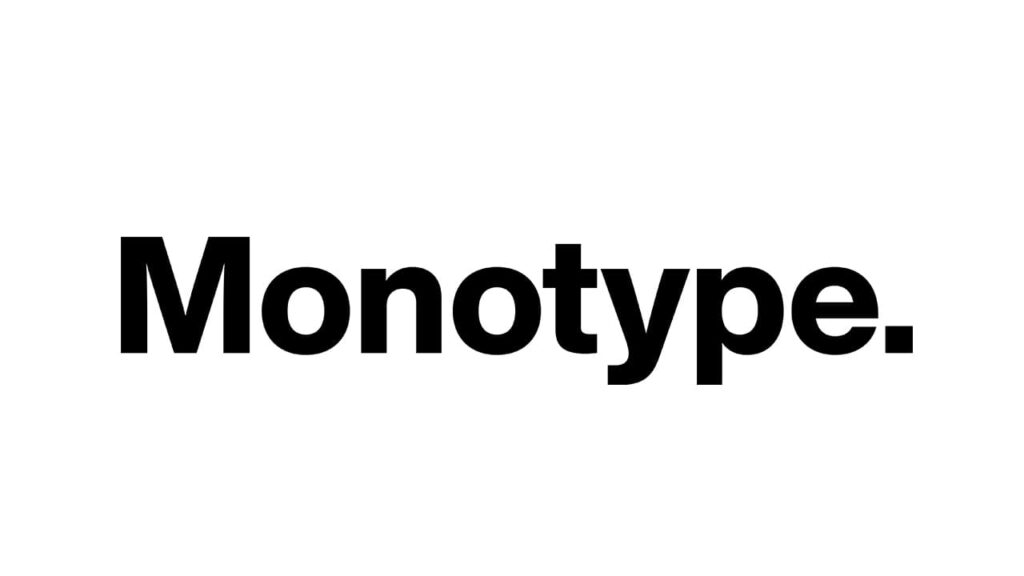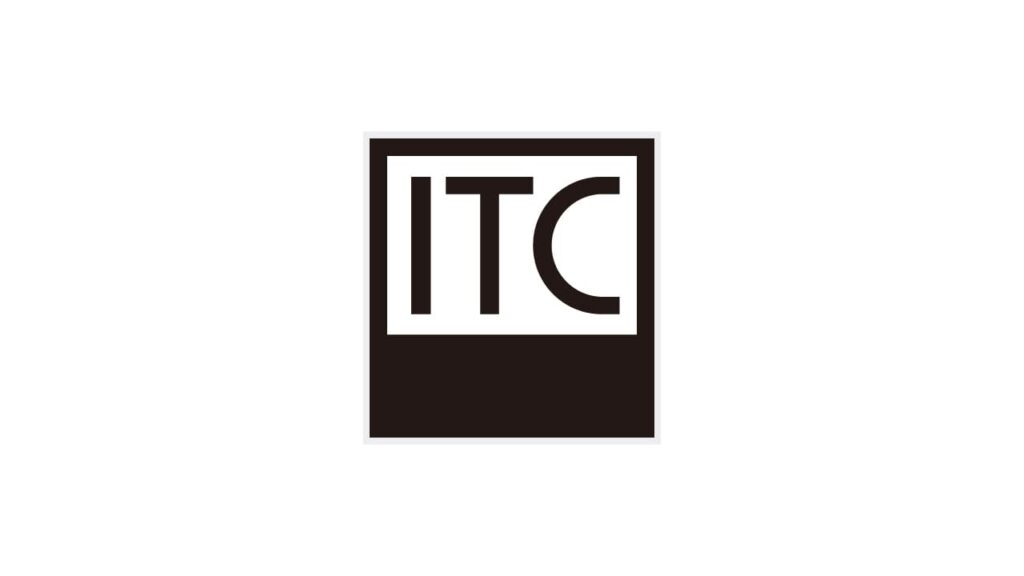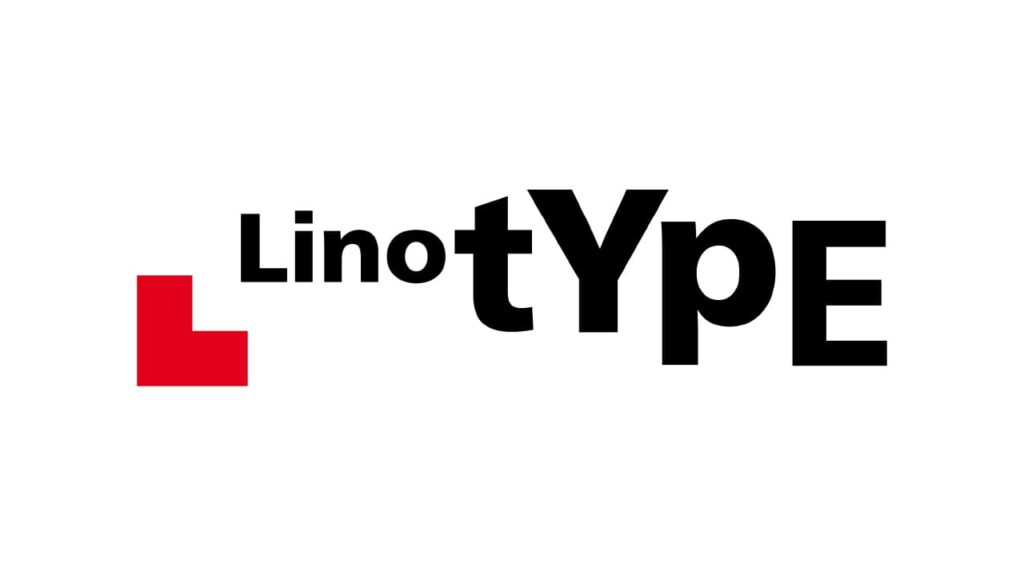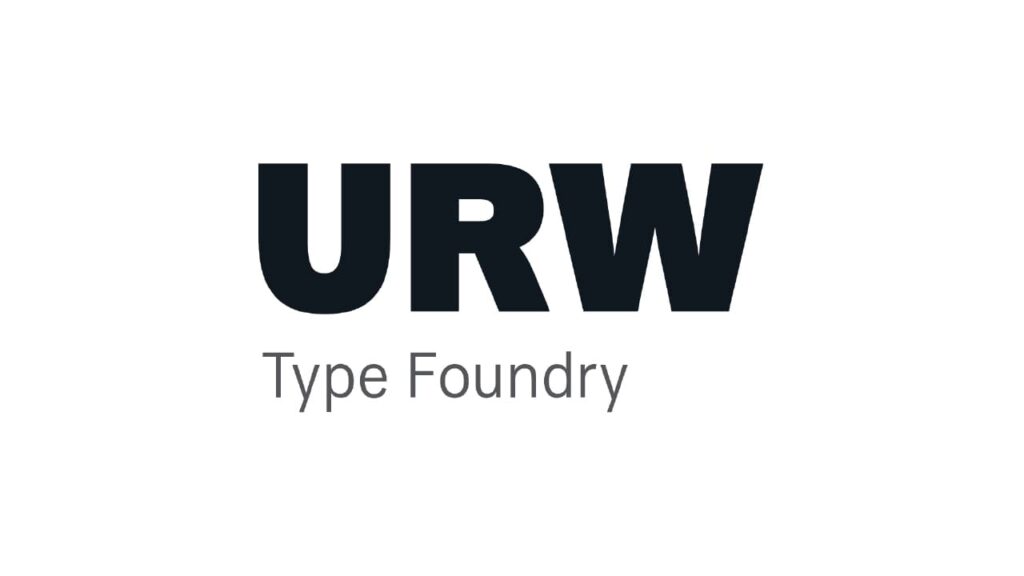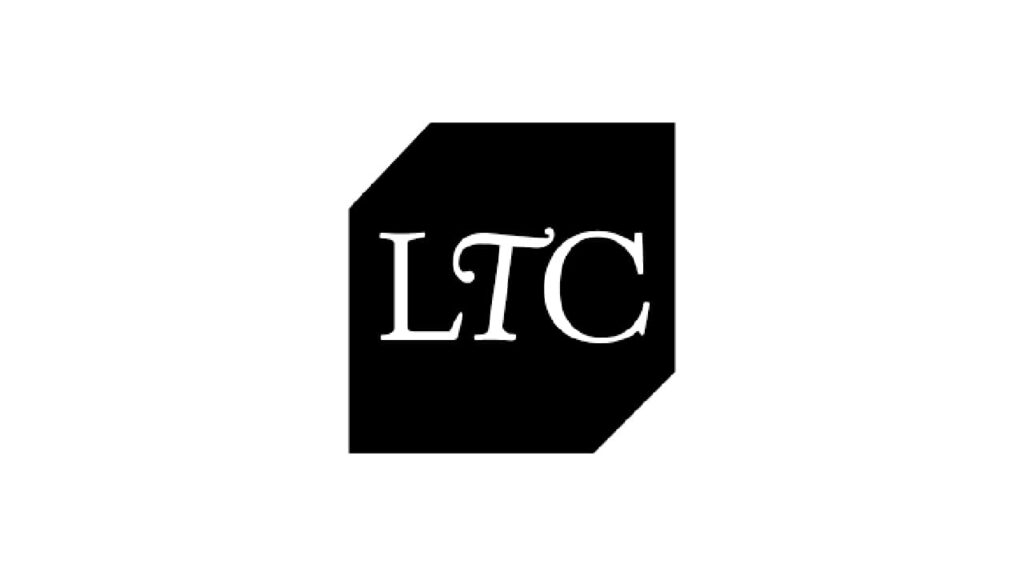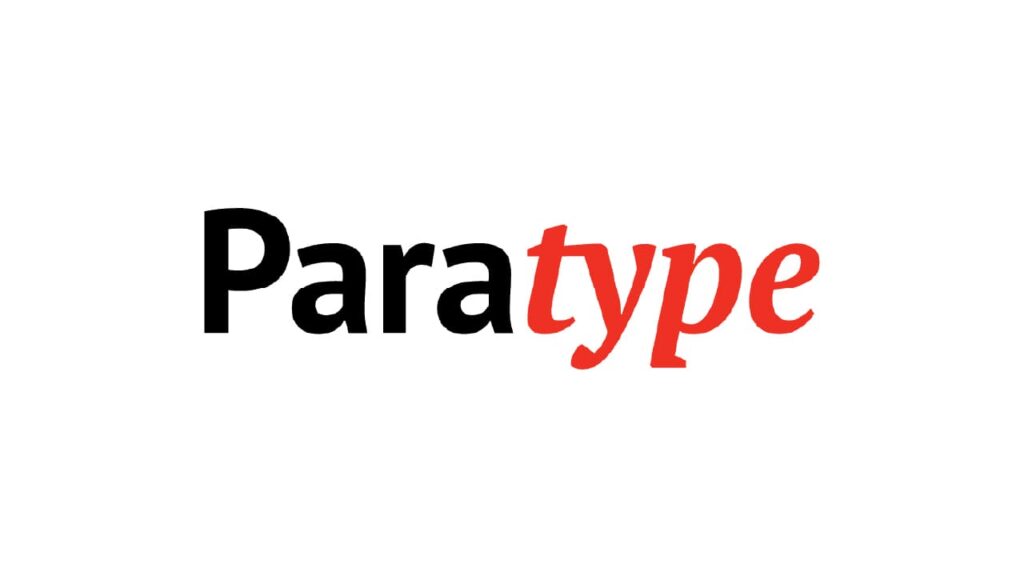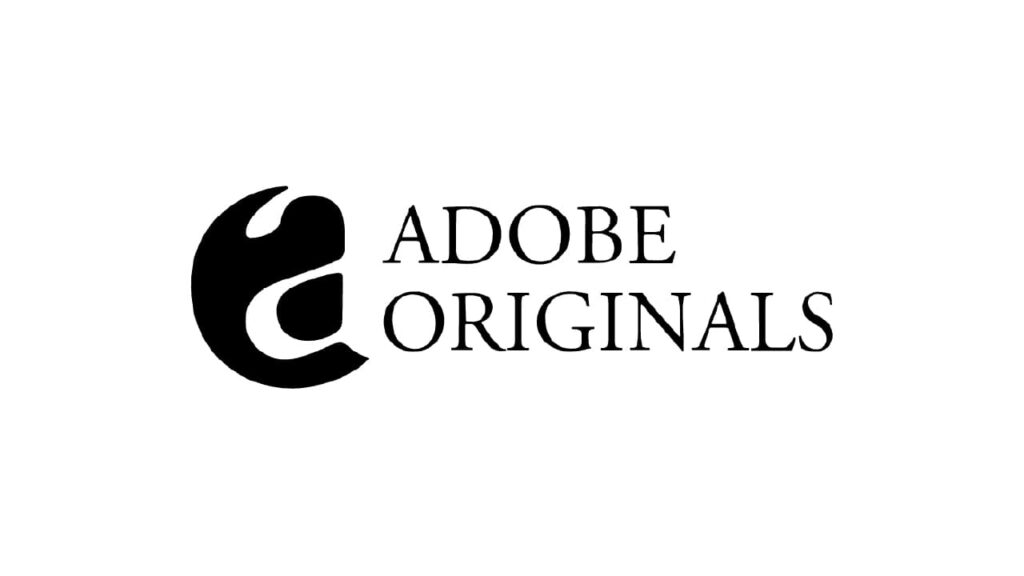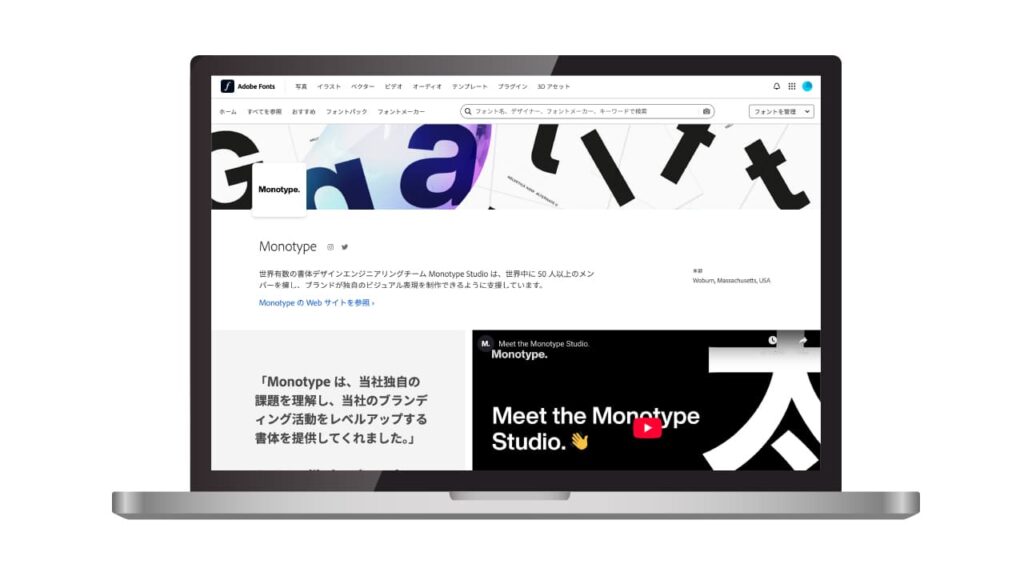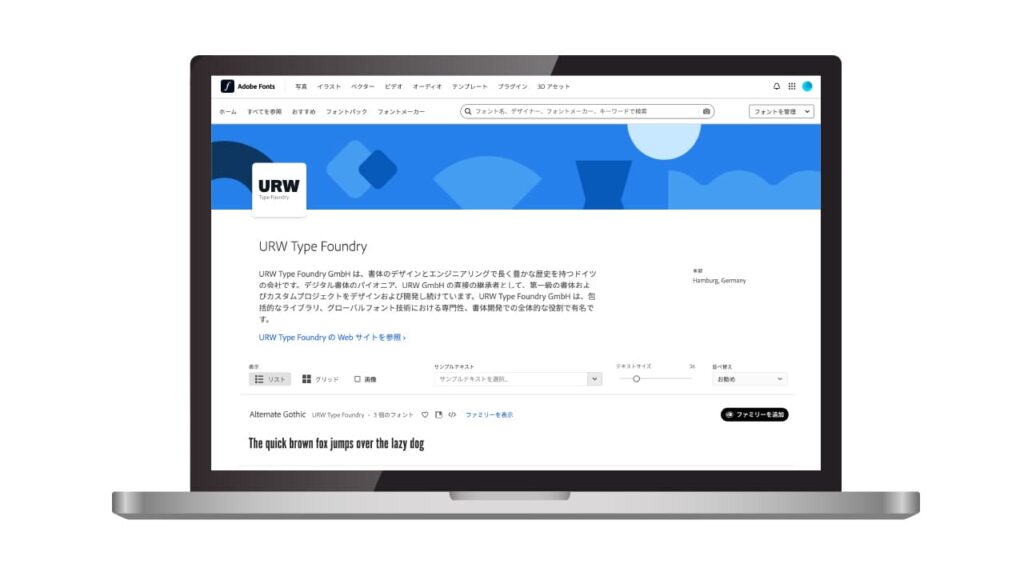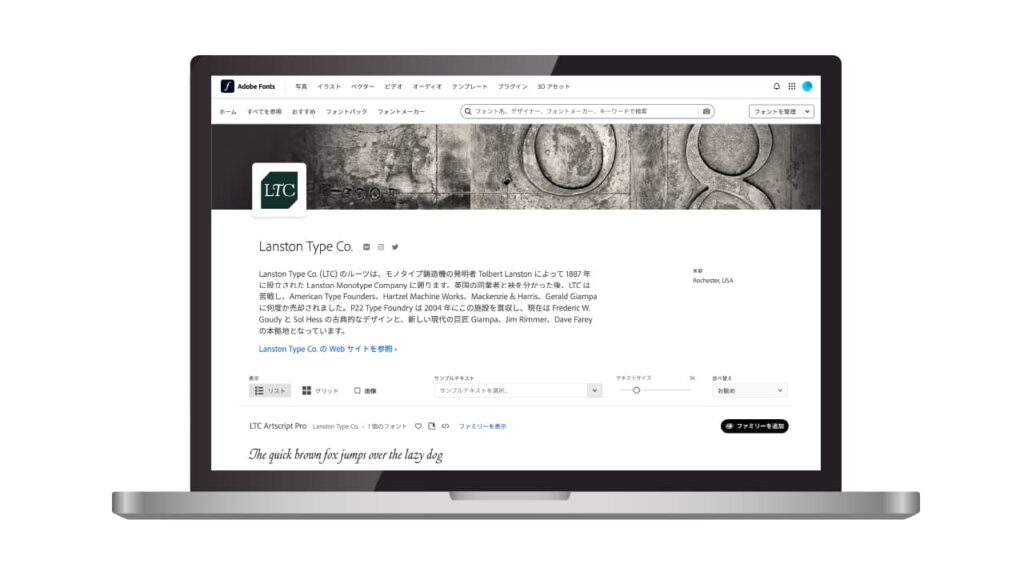
デザイン初心者やデザイナー志望学生向けに、Adobe Fontsでよく目にする主要なフォントベンダー(書体メーカー)についてまとめました。Adobe Fontsを使っていると、「同じ書体だけど種類がたくさんあるのはなぜ?」「同じ名前の書体なのに違うベンダー名が付いている…どれを使えばいいの?」と混乱することがありますよね。この記事では Monotype、ITC、Linotype、URW、LTC(Lanston Type Co.)、Paratype、Adobe Originals の7つに注目し、それぞれの歴史や特徴、代表的な書体と用途例、業界の背景(MonotypeとITCの買収関係など)、Adobe Fonts上での扱われ方、そして初心者が書体選びで混乱しないコツをカジュアルに解説します。ボリュームは多めですが、これを読めばフォントベンダーによる書体の違いがスッキリ理解できるはずです。
フォントベンダーって何?
フォントベンダーとは、書体を制作・販売しているメーカーのこと。
Adobe Fontsでは、世界各国の様々なフォントベンダー(フォントメーカー)とパートナーシップを結び、何千ものフォントを提供しています。ここでは特に、初心者が知っておくと役立つ主要なベンダー7社を紹介します。それぞれの歴史的背景や特徴、Adobe Fonts上で提供されている代表書体、そして書体デザイン上の傾向などを見ていきましょう。
同じ書体名で異なるフォントが存在する理由
まずは一番の疑問、「なぜ同じ名前の書体が複数存在するのか?」についてです。実は書体の世界では、歴史的な名作フォント(例えばガラモン、ボドニ、カスロンなど)のデザインが、長い年月の中で多くの会社やデザイナーによって復刻・改刻されてきました。それぞれの復刻版はオリジナルに対する各社独自の解釈が反映されており、微妙にデザインが異なるため、厳密には別のフォントと言えます。
ところが困ったことに、そうした復刻フォントは名前が似通っている場合が多いのです。オリジナルの有名な名前に、接頭辞や接尾辞を付け加える程度で区別しているケースがほとんどだからです。例えばBodoniという書体には、ITC Bodoni、URW Bodoni、Monotype Bodoni、Berthold Bodoni、WTC Bodoni…など本当にたくさんのバージョンがあります。Caslon(キャスロン)という書体も、Adobe Caslon、ITC Caslon、LTC Caslon、Caslon 540など多数の版が存在します。
書体の復刻版は、まるで同じ曲をカバーする別々のアーティストのようなものです。同じメロディー(書体デザイン)でも、ジャズ風アレンジやロック風アレンジがあるように、フォントも作り手によって味付けが異なります。しかし曲名(書体名)は共通しているので紛らわしい…というイメージです。
Adobe Fontsでは、こうした同名異フォントを扱うために、多くの場合フォント名にベンダー名(メーカー名)や略号を付与しています。例えば「Baskerville」という書体は以下のように複数あります。
• Baskerville URW – ドイツのURW社による復刻版バスカヴィル
• Baskerville PT – ロシアのParatype社による復刻版バスカヴィル
• Baskerville と Baskerville No.2 – Monotype社(もともとBitstream社)によるバスカヴィル
このようにAdobe Fonts上では名前である程度区別されていますが、それでも「どれを選べばいいの?」と迷うことがありますよね。そこで次章から、主要ベンダーそれぞれの特徴と代表的な書体、そしてどんなときにそのベンダーのフォントを選ぶとよいかを解説していきます。
知っておきたい主要ベンダー
Monotype(モノタイプ)
概要
Monotype(モノタイプ)は、世界的なフォントメーカーとして知られる企業であり、数多くの著名なフォントブランドを傘下に持つ大手企業です。起源は1887年にアメリカで創業した活字鋳造機メーカー「ランストン・モノタイプ社」に遡ります。20世紀にはTimes New RomanやGill Sans、Arialといった定番フォントを開発し、業界における確固たる地位を築いてきました。デジタル化の進展に伴い、Linotype、ITC、Bitstream、FontFont(FontShop)、URW、Hoefler&Coなどの有力フォントメーカーを次々に買収。これにより、MonotypeはHelveticaやPalatino、Gothamなど、世界的に使用される書体の多くの権利を保有するに至っています。
代表書体
Monotypeが所有または提供している代表的な書体には、以下のようなものがあります。
• Gill Sans:英国的でエレガントなサンセリフ体
• Bembo:ルネサンス期の古典様式を踏襲した書体
• Century Gothic:幾何学的構造を特徴とするモダンサンセリフ体
• Helvetica:現代デザインにおける定番中の定番サンセリフ体
• Palatino:読みやすさに優れたセリフ体
• Gotham:モダンかつ信頼感のある印象を与えるサンセリフ体
これらの書体は、Adobe Fontsをはじめとした各種プラットフォームでも利用可能であり、デザイン現場で広く活用されています。
特徴
• 豊富な書体資産
Monotypeは長年にわたりフォント業界の主要企業を買収・統合してきた結果、クラシックからモダンまで幅広いスタイルのフォントを揃えています。
• 品質の安定性
プロフェッショナル向けフォントとしての品質が高く、視認性や可読性に優れており、印刷・Webいずれの用途にも適しています。
• Adobe Fontsとの連携
Monotypeが提供する多くのフォントは、Adobe Fontsでも利用可能であり、デザイナーにとって利便性の高い選択肢となっています。フォント名に「MT」や「Monotype」と明記されていない場合でも、詳細情報に提供元として記載されています。
• 初心者にも扱いやすい
デザイン初心者にとっても使いやすく、オーソドックスなスタイルのフォントが多いため、学習用途や実務における初期導入にも適しています。
ITC(International Typeface Corporation)
概要
ITC(International Typeface Corporation)は、1970年にニューヨークで設立されたフォント専門会社であり、金属活字時代を持たない、新時代のフォトレタリング(写植)技術を基盤に誕生しました。設立には著名なグラフィックデザイナー、ハーバート・ルバリンをはじめとする先進的なクリエイターが関与しており、フォントデザインの革新を牽引してきました。ITCは、新規の書体開発に加え、既存の古典的書体を現代的にリデザインすることを得意とし、1970〜80年代のグラフィックデザインに大きな影響を与えました。現在ではMonotype社の傘下にあり、その書体群はAdobe Fontsを通じて広く提供されています。
代表書体
ITCによる代表的な書体は、独自の美意識とタイポグラフィの革新性を体現しています。以下に主要な例を挙げます。
• ITC Avant Garde Gothic:幾何学的構造と前衛的デザインが特徴のサンセリフ体
• ITC Garamond:極端にxハイトを拡大した、カジュアルで現代的なガラモン体
• ITC Bodoni:用途に応じた光学サイズ別のデザインが施されたモダンなボドニ体
• ITC Bookman:柔らかな印象に再構成されたブックマン体
• ITC Franklin Gothic:オリジナルに比べてバランスを再設計した、力強いゴシック体
• ITC Souvenir:レトロで親しみやすい印象を与えるセリフ体
これらの書体は、デザインにおいて個性や懐かしさ、視覚的なインパクトを演出したい場面に適しています。
特徴
• xハイトの拡大
ITC書体の大きな特徴として、小文字(xハイト)の高さが著しく拡張されている点が挙げられます。これにより、小さなサイズでも視認性が高く、タイトルや見出しなどでの使用に適しています。
• 多彩なウェイト展開
多くのITC書体は複数の太さ(ウェイト)を備えており、デザインにおける柔軟な表現を可能とします。
• 現代的リデザイン
既存の古典書体を大胆に再構築したスタイルが多く、従来の書体とは一線を画す個性的な印象を与えます。
• レトロモダンな表現に最適
1970〜80年代のグラフィックデザインで広く使用されたことから、レトロポップやモダンヴィンテージといったスタイルにおいて特に効果を発揮します。
• Monotype傘下での展開
現在はMonotypeがブランドを継承しており、Adobe Fonts上でも「ITC」の表記がある書体として確認可能です。
現在ではMonotype社の傘下にありますので、Monotype内で確認できます。
Linotype(ライノタイプ)
概要
Linotype(ライノタイプ)は、1886年にアメリカで発明された鋳植機「ライノタイプ」の製造会社として創業した、伝統ある活字メーカーです。同機の登場により、従来の手作業による活字組版に代わる効率的な印刷技術が実現され、印刷業界に革新をもたらしました。20世紀以降、Linotype社は欧米を中心に多くの書体を展開し、その中にはタイポグラフィ史に残る名作が数多く含まれます。特にスイスやドイツの著名なタイポグラファーによってデザインされたフォント群は、現在でも多くのデザイン現場で用いられています。2000年代にはMonotype社に買収され、現在ではその傘下にありますが、Adobe Fontsでは「Linotype」ブランドとして引き続き提供されており、クラシックフォントの代表的な存在として広く認知されています。
代表書体
Linotypeが提供している主要な書体は、タイポグラフィの歴史において極めて重要な位置を占めています。以下に代表的な書体を挙げます。
• Helvetica(ヘルベチカ):モダンデザインの象徴ともいえる、普遍的でバランスの取れたサンセリフ体
• Univers(ユニバース):構造的で整理された印象を与える幾何学系サンセリフ体
• Frutiger(フルティガー):空港や公共サインにも採用される、可読性に優れたヒューマニストサンセリフ体
• Palatino(パラティーノ):クラシカルで読みやすく、長文にも適したセリフ体
• Optima(オプティマ):セリフとサンセリフの中間のようなニュアンスを持つ、上品なフォント
特徴
• タイポグラフィの名作が多数
HelveticaやFrutigerなど、タイポグラフィの教科書にも登場するような名作フォントが揃っています。
• ヨーロッパの著名デザイナーによる設計
アドリアン・フルティガー、ヘルマン・ツァップなど、書体設計の巨匠たちの作品が多く含まれています。
• Monotype傘下での継続提供
2000年代以降Monotypeに統合されつつも、「Linotype」ブランドはAdobe Fonts上でも維持されており、同名のフォントが引き続き利用可能です(フォント名に「LT」や「Linotype」と記載されている場合が多い)。
• 初心者にも扱いやすいラインナップ
バランスの良い構造や高い可読性により、タイポグラフィに不慣れなユーザーでも安心して使用できます。
• 古典の復刻版も充実
Linotype独自のアプローチで復刻されたBaskervilleやGaramondなどのクラシックフォントも使用でき、歴史的文脈を意識したデザインに適しています。
Adobe Fontsで確認しよう
現在ではMonotype社の傘下にありますので、Monotype内で確認できます。
URW Type Foundry(URW)
概要
URW(Unternehmensberatung Rubow Weber)は、ドイツに本社を置くフォントメーカーで、その社名の頭文字を取ってURWと称されています。1970年代よりデジタルフォント技術の先駆者として知られ、特にフォントアウトラインデータを扱う「Ikarusシステム」の開発に関わるなど、技術面で大きな影響を与えてきました。500以上のフォントファミリーを有し、クラシック書体のデジタル復刻からオリジナル書体、多言語対応書体、企業向けカスタムフォントまで、幅広いフォント開発を手がけています。近年ではオープンソースフォントへの貢献も行い、Adobe Fontsをはじめとする多数のプラットフォームでそのフォントが利用されています。
代表書体
URWが提供する書体は、復刻フォントからオリジナルフォント、そしてオープンソース版まで多岐に渡ります。以下はその代表例です。
• URW Bodoni:アメリカ的要素を加味した、独自のボドニ復刻版
• URW Garamond:伝統的なガラモンを現代的に再構成したスタイル
• URW Clarendon:クラレンドン系の標準的なセリフ体
• URW Grotesk:ヘルマン・ツァップによるURWオリジナルの汎用サンセリフ
• Nimbus Sans:Helveticaに相当するサンセリフ体のURW版(オープンソース)
• Nimbus Roman:Timesに相当するセリフ体のURW版(オープンソース)
これらのフォントはAdobe Fontsでも多く採用されており、「URW」の表記がついたものとして簡単に識別することができます。
特徴
• 技術革新の先駆者
1970年代からデジタルフォント技術に取り組み、Ikarusなどのアウトライン処理技術に貢献した実績があります。
• クラシックフォントの復刻と発展
BodoniやGaramondなどの歴史的書体をURW流にアレンジして提供。場合によっては原典から大きくデザインを変更しているものもあります。
• オープンソースへの貢献
Ghostscriptなどのソフトウェアにおいても活用されるNimbusシリーズをはじめ、PostScript基本35書体の代替フォントを無償提供したことで知られています。
• 多言語・カスタム対応に強い
ラテン文字以外の多言語対応書体や、企業ブランディング向けのカスタムフォント開発においても高い評価を受けています。
• Adobe Fontsでの提供
多くのURWフォントがAdobe Fontsで利用可能となっており、「URW」表記があるフォントはその提供元を示しています。特に本文用途に適したベーシックな書体が多く揃っている一方で、一部フォントは古いデジタル化方式ゆえに細かな組版機能が省略されているケースもあります。
Adobe Fontsで確認しよう
Lanston Type Co.(LTC)
概要
Lanston Type Co.(LTC)は、1887年にアメリカで創業された「Lanston Monotype(ランストン・モノタイプ)」の流れを汲む歴史あるフォントメーカーです。イギリスのMonotype社とは別組織として発展し、アメリカ国内ではATF(アメリカン・タイプ・ファウンダーズ)社や複数の企業による買収を経て存続してきました。最終的にはカナダのタイポグラファー、Gerald Giampa氏が継承し、2004年にP22 Type Foundry社が買収。現在はP22社のコレクションブランドとして機能しており、クラシックな活字文化を受け継ぐ書体群を提供しています。LTCは、Frederic GoudyやSol Hessなど往年の著名デザイナーによる名作をデジタル化し、その歴史的価値の保存と継承に貢献しています。
代表書体
LTCが提供する書体は、歴史的資料に基づき忠実に再現されたものが多く、以下のようなクラシック書体が代表的です。
• LTC Bodoni 175:1790年の原活字をSol Hessが機械植字向けに復刻し、AdobeのPaul Hunt氏がデジタルリマスター。オリジナルに近いエレガントなディド体
• LTC Caslon:18世紀英国のWilliam Caslonによるセリフ体の復刻版。温かみと読みやすさを兼ね備えるクラシックフォント
• LTC Goudy Oldstyle:Frederic Goudyがデザインした、アメリカン・オールドスタイルセリフ体の代表作。上品で親しみやすい印象
• LTC Cloister:中世写本の書体に着想を得た、伝統的かつ荘厳な雰囲気のセリフ体
• LTC Kennerley:Goudyによる文学的で繊細な表情を持つ書体。本文組に適した安定感ある佇まい
これらの書体はすべてAdobe Fontsでも提供されており、「LTC」または提供元が「Lanston」と記載されていることで判別可能です。
特徴
• クラシック回帰の思想
LTC書体は活字印刷全盛期の書体をベースに、忠実かつ丁寧にデジタル化されており、「印刷文化の香り」を感じさせる仕上がりが魅力です。
• オーセンティックなデザイン
同じ書体名であっても、URW版やITC版などと比べて、よりオリジナルに忠実な設計がなされており、本文組にも最適な落ち着いた雰囲気を持ちます。
• 歴史的名作のデジタル保存
GoudyやHessといった歴史的書体デザイナーの作品を現代に蘇らせ、その芸術的価値を保持。タイポグラフィ研究にも適しています。
• Adobe Fontsで利用可能
多くのLTC書体はAdobe Fontsで利用でき、古典的な書体を気軽に実務で使うことができます。
• ベーシックな文字セット
一部フォントでは記号類や拡張文字セットが限定的な場合があり、用途に応じて補完が必要となるケースもあります。
クラシックな印象を演出したいデザインや、タイポグラフィの歴史に基づいたフォント選びを重視する方にとって、LTCは非常に魅力的な選択肢となります。
Adobe Fontsで確認しよう
Paratype(パラタイプ)
概要
Paratype(パラタイプ)は、1989年にモスクワで設立されたロシアを代表するフォントベンダーです。その起源は、旧ソ連時代に国営のフォント開発機関として機能していたPolygraphmash(ポリグラフマッシュ)にあり、独立後も同機関の豊富なキリル文字書体資産を継承しています。創設者はエミール・ヤクーポフ氏。設立以降、Paratypeはデジタルフォントの開発に注力し、多言語対応フォント、特にキリル文字を含むマルチスクリプトの分野で高い評価を獲得してきました。
中でも、ロシア政府の依頼により制作されたPT Sans / PT Serifは、オープンソースで公開された高品質フォントとして世界的に知られており、Paratypeの代表作となっています。
代表書体
Paratypeが開発または提供している代表的な書体には、以下のような多言語・高機能フォントがあります。
• PT Sans / PT Serif:キリル文字・ラテン文字の両方に対応し、ロシア語圏を中心に多言語環境で使用されるオープンソースフォント
• Futura PT:クラシックなFuturaにキリル文字を追加した復刻版。モダンかつ実用的な設計
• Baskerville PT:伝統的なBaskervilleをベースにしつつ、「Poster」「Display」などのウェイトも備えたタイトル用途向けフォント
• Humanist 521(旧Gill Sans):Gill Sansをリファレンスとしたデザインにキリル文字を組み合わせた高可読フォント
• Paratype Serif / Paratype Sans:独自に開発されたモダンなセリフ体・サンセリフ体。特にビジネス用途に適した印象
Adobe Fonts上では、フォント名に「PT」と付くものがParatype社のフォントであることが多く、それによって提供元を判別することが可能です。
特徴
• マルチスクリプト対応の先駆者
Paratypeの最大の強みは、ラテン文字とキリル文字を高い品質で統合したフォント設計にあります。多言語環境に対応するフォントが必要な場面で非常に有効です。
• 読みやすさと機能性の両立:Paratypeのフォントは、視認性と実用性を重視した設計が多く、本文用・見出し用問わaず使いやすいデザインとなっています。
• 独自の美意識と温かみ
洗練された西欧的デザインと、ロシア的な無骨さや柔らかさが同居しており、他のフォントベンダーにはない独特の表情を持っています。
• 豊富なウェイト展開とスタイル
Paratype版フォントには、細かな用途に対応したスタイルが含まれている場合が多く、たとえばBaskerville PTのように「Poster」「Display」などタイトル向けの細身ウェイトが揃っている点が特長です。
• Adobe Fontsでも提供
PT SansやPT SerifをはじめとしたParatypeフォントはAdobe Fontsでも多数利用可能です。多言語対応が求められるデザインや、個性を演出したい場面で有力な選択肢となります。
Paratypeのフォントは、国際的なコミュニケーションや多文化環境でのデザインに強く、可読性・機能性・美しさを兼ね備えた優れたフォントを探している方にとって有用です。
Adobe Fontsで確認しよう
Adobe Originals(アドビ・オリジナルズ)
概要
Adobe Originals(アドビ・オリジナルズ)は、Adobe社が自社開発したフォントブランドであり、1989年に社内のフォント開発プログラムとして始動しました。その設立目的は、「卓越したデザインクオリティ」「高い技術的信頼性」「時代を超えて使える美しさ」を兼ね備えた書体の創出にあります。
Adobeの書体チームは、設計者・研究者・技術者から構成されており、長年にわたるタイポグラフィへの深い理解と高度な技術を活かして、多数の優れたフォントを開発してきました。これらのフォントは、プロフェッショナルから初心者に至るまで幅広い層に支持されており、業界標準として高く評価されています。
代表書体
Adobe Originalsの中でも特に評価の高いフォントは以下のとおりです。
• Minion Pro:1989年にRobert Slimbachによって開発されたセリフ体。読みやすく、書籍や雑誌、Webなど幅広い媒体で使用される汎用書体
• Myriad Pro:Carol Twomblyらによって設計されたヒューマニストサンセリフ体。Apple社の旧コーポレートフォントとしても知られ、明快で現代的な印象
• Adobe Garamond Pro:クラシックなGaramond書体をベースに、Adobeが独自に復刻・洗練させた品格あるセリフ体
• Trajan:ローマ時代の碑文に基づいた大文字専用の書体。映画ポスターなどでよく用いられる荘厳なデザイン
• Source Han Sans / Serif(源ノ角ゴシック・源ノ明朝):AdobeとGoogleの協力により開発されたCJK(中・日・韓)対応のオープンソース多言語フォント。漢字文化圏のタイポグラフィに革命をもたらした高品質フォント
特徴
• Adobe社による高品質保証
Adobe自身が設計・保守しているため、技術的な信頼性が高く、アップデートや互換性にも優れています。Creative Cloud利用者であれば、常に利用可能な安心感もあります。
• 幅広い用途に対応
本文用・見出し用・タイトル用など、多様な目的に応じた設計がなされており、どのようなプロジェクトでも活用しやすいフォント群が揃っています。
• 多言語対応と国際性
欧文だけでなく、日本語や中国語、韓国語を含むCJKフォントの開発にも注力しており、多文化環境での使用に適しています。
• デザイン性と可読性の両立
視認性を損なうことなく、美しさと品格を兼ね備えた設計がなされており、初心者にも扱いやすいのが特長です。
• Adobe Fontsで常時利用可能
Adobe Originalsの書体は、Adobe Fonts上で常に提供されており、Creative Cloud加入者は追加費用なしで使用できます。
Adobe Originalsは、「とりあえずこのフォントを使っておけば安心」と言えるほど汎用性が高く、フォント選びに迷った際の第一候補として最適です。デザイン初心者の入門書体としても、プロフェッショナルの現場でも、高い信頼性を発揮するブランドです。
Adobe Fontsで確認しよう
初心者が書体選びで混乱しないための5つのコツ
1. ベンダー名を意識する(略称やメーカーを確認)
同じような名前の書体が並んでいたら、まずフォント名に含まれるベンダー(メーカー)名や略称に注目してください。例えば「◯◯ Pro」や「MT」「LT」「ITC」「PT」「LTC」などの記号があれば、それがそのフォントの出自を示しています。慣れないうちは「このフォントはどこの会社が作ったものかな?」と調べてみると発見があります。ベンダーの歴史を知るとデザインの背景が見えてきて面白いですよ。
2. 用途に合わせて選ぶ(本文用か見出し用か)
迷ったときは、その書体がどのような用途に向いているデザインかを考えましょう。例えばITC系は見出し向けで派手め、大きなサイズで映える傾向があります。一方でAdobe OriginalsやMonotype系のクラシック書体は本文組版に適した落ち着いたデザインが多いです。もし長文の本文に使うならオープンタイプ機能が充実したPro版(スモールキャップや旧字形を備えたもの)を選ぶのがおすすめです。逆にタイトルロゴなどインパクト重視ならITCやURWのユニークな書体も活きるでしょう。
3. 実際に組んで比較する(微妙な違いを目で確認)
Adobe Fontsでは同じ文章でフォントをプレビューできます。気になる書体が複数あれば、実際にテキストを打ち込んで表示し、違いを比較してみましょう。同じ「Garamond系」でも字面の雰囲気や可読性が異なるはずです。初心者のうちは違いが掴みにくいかもしれませんが、じっくり見ると「こっちの方が数字が見やすいな」など発見があります。それでも迷う場合は、一般的に評価の高い定番フォントを選んでおけば大きな失敗はありません。例えば本文ならAdobe GaramondやMinion、見出しならHelveticaやFuturaなど、歴史的に実績のある書体は安心感があります。
4. 混ぜすぎに注意(1プロジェクトで書体を絞る)
書体選びに慣れないうちは、一つのデザイン内であれもこれもと多くのフォントを混在させないこともポイントです。同じファミリー内で太さを変える程度に留め、異なる書体はせいぜい2種類までにすると統一感が出ます。また、同じ名前の別ベンダー版フォントを同時に使うのは避けましょう。例えば「Bodoni」を2種類アクティベートしてしまうと、ソフト上で置き換わってしまったり表示が混乱する可能性があります(Adobe Fonts上ではうまく区別されますが、念のため)。基本的には一つのプロジェクトにつき各書体は1バージョンに絞る方が安全です。
5. 楽しみながら学ぶ(いろんな書体を試す)
最後に、フォント選びは楽しむことが大事です!最初は難しく感じるかもしれませんが、色々な書体の歴史や特徴を知るとタイポグラフィの世界がぐっと広がります。Adobe Fontsでは幸いにも世界中のフォントを試せる環境が整っています。ぜひ怖がらずに色んなベンダーの書体を触ってみて、自分のお気に入りを見つけてください。その過程で「この書体の雰囲気いいな」「どうしてこのフォントは読みやすいんだろう?」と感じたら、今回紹介したベンダーの背景を思い出してみましょう。きっと書体デザインへの理解が深まり、より適切なチョイスができるようになるはずです。